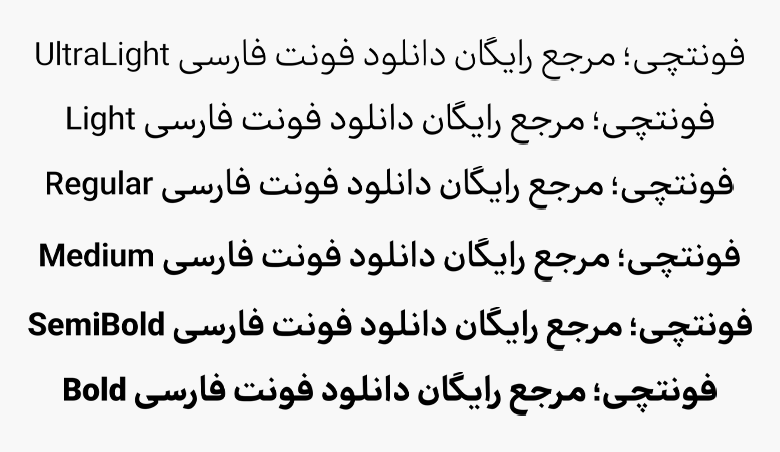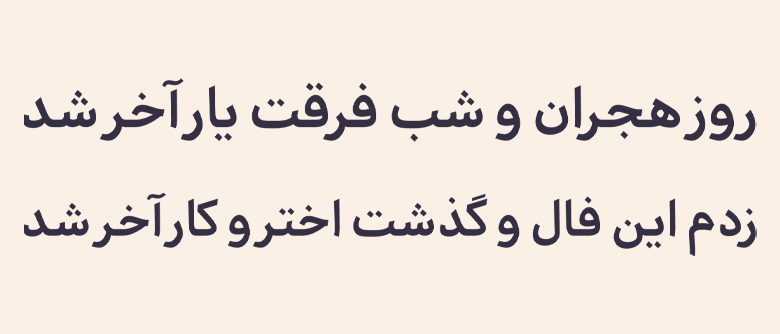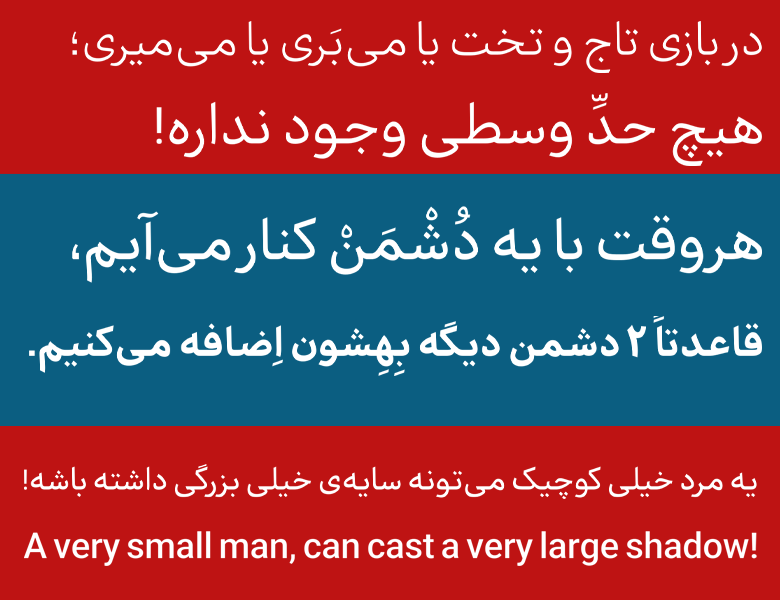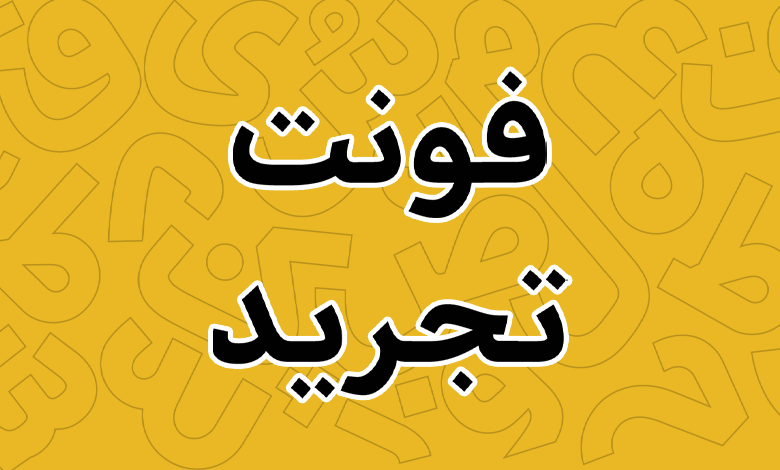
فونت تجرید (Tajrid)
فونت تجرید (Tajrid) یک فونت متن فارسی و عربی است که بر پایه خط نسخ در سال ۱۳۹۲ توسط رضا غفاری طراحی شده و در نهایت در سال ۱۳۹۹ جهت استفاده عمومی منتشر گردیده است. در طراحی این فونت هدف افزایش خوانایی بوده که برای استفاده در متنهای بلند و ساختارهایی که بر اساس اسکرین هستند مناسب باشد؛ از همین رو اگر قرار باشد لیستی از بهترین فونت های وب فارسی داشته باشیم، تجرید یکی از این فونتها است.
در دورهای که فونت تجرید طراحی گردیده بود، فونتهای مناسب وب به تعداد بسیار محدودی بودند که این نیاز همواره برای داشتن فونتی که برای متون فارسی و عربی ساختاری یکپارچه فراهم کند احساس میشد. البته چنین چیزی به این معنی نیست که سایر فونتها این نیازها را برطرف نمیکرد؛ بلکه منظور این است که فونتی که تنظیم نسبت ارتفاع و اندازه حروف و کرسیها در یک ثبات باشد، به تعداد بسیار محدودی بود.
در ادامه این نوشته از سایت فونتچی به نقد و بررسی کامل فونت فارسی نجرید خواهیم پرداخت که علاوه بر این زبان، ساختار بسیار استانداردی با سایر زبانهای خاورمیانهای همچون عربی و اردو دارد. این فونت که دارای ساختاری با پهنای ثابت در بخش اعظم حروف است در ۶ وزن طراحی گردیده است.
معرفی و بررسی فونت تجرید (Tajrid)
در همان نگاه اولی که به فونت تجرید داشته باشید، این حس را منتقل میکند که با یک فونت خاکستری مواجه هستیم. تفاوتی هم ندارد که از کدام وزن این فونت استفاده کنید؛ در تمامی وزنها الگوی کلی این حس را منتقل میکند و به مقدار بسیار محدودی در وزنهای ضخیم از این حس کاسته میشود.
از طرفی دیگر این فونت دارای کنتراست کمتری نسبت به سایر فونتهای متن است و این دقیقا همان چیزی است که در بیشتر فونتهای اینچنین، برخلاف فونتهایی که مناسب عنوان و تبلیغات هستند شاهد آن هستیم.
وزن و استایل فونت تجرید
همانطور که گفتیم فونت تجرید از ۶ وزن پشتیبانی میکند که شامل وزنهای «خیلی نازک، نازک، معمولی، متوسط، نیمه بولد و بولد» است. این فونت بر خلاف سایر فونتهای متن، در تمامی وزنها دارای گلیفهای لاتین است که در یک قلم منفرد (تکی) میشود متن را در هر دو زبان لاتین و فارسی تنظیم کرد.
کاراکترهای اصلی زبان لاتین انگلیسی در این فونت قرار دارد و از همه زبانهایی نظیر عربی، کردی و اردو که از خط فارسی استفاده میکنند نیز پشتیبانی میکند.
ویژگی و امکانات فونت Tajrid
تجرید فونتی مناسب متن است و تفاوتی ندارد که در یک متن کوتاه و عنوان عمچون شعارهای تبلیغاتی از آن استفاده کنید یا اینکه در متنهای بسیار بلند همچون صفحات وب یا چاپ کتاب از این فونت بهره ببرید. در هر حالتی و در همه وزنها، فونت تجرید نیاز شما را برطرف کرده و با توجه به ساختار عالی که از نظر خوانایی دارد، بهترین کارکرد را در دسته فونتهای مناسب متن دارد.
این فونت جدای از مشخصات فوق دارای برخی ویژگیها همچون ترکیبات جایگزین، پشتیبانی از اعداد فارسی و استفاده در انواع وب و اپلیکیشن است که پیش از دانلود فونت تجرید بد نیست نگاهی به آنها نیز داشته باشید.
پشتیبانی از ۴ زبان مختلف
تجرید فونتی است که بر اساس استاندارد جهانی یونیکد طراحی شده است. تمامی گلیفهایی که به هر ساختار حروف و کاراکترها استفاده میشود، برای هر زبان یکه هستند که در این فونت در قالب یک فایل منفرد پیادهسازی گردیده است.
فونت تجرید فارسی برای زبانهای خاورمیانهای یک حالت پیشفرض است که از همینرو کلیه زبانهایی که مبتنی بر حروف فارسی هستند را هم پشتیبانی میکند که از جمله آنها میتوان به زبانهای عربی، کردی و اردو اشاره کرد.
در خصوص زبانهای لاتین همچون انگلیسی نیز همین ساختار یکپارچه و در قالب یک فونت منفرد پیاده سازی شده است که در حالت کلی شما با نصب یک فونت منفرد، میتوانید به تمامی کاراکترهای فارسی، انگلیسی و سایر زبانهایی که این فونت پشتیبانی میکند دسترسی داشته باشید.
مجموعهای از اعداد جداول اروپایی (لاتین) و سمبلها نیز در این فونت پیادهسازی شده که بر اساس صفحه کلید انتخابی، زبان یا استفاده از charmap در سیستم عامل میتوانید به این ترکیبات نیز دسترسی داشته باشید.
دارای حروف و ترکیبات جایگزین
این فونت در برخی حروف دارای چند ساختار مختلف است که میتوانید به شکل متفاوتی چنین حروفی را طراحی کنید. حروفی همچون «الف، ه و ی» در این فونت از چند حالت مختلف پشتیبانی میکنند که برای زبان فارسی و سایر زبانهای خاورمیانهای امکان تایپ کلمات را در چند حالت به شما خواهند داد که میتواند در میحث طراحی روی پیادهسازی خلاقانه متون موثر باشد.
در زبان عربی این ترکیبات در حالتی که در حروف «ه، ی» که دارای دو نقطه در زیر یا بالا هستند نیز وجود دارد که استاندارد بین المللی در آن رعایت شده باشد.
جدا از حروف، برخی ترکیبات نیز از این ساختار پشتیبانی میکنند که برای حروف «ـه، ـی» قابل استفاده است. کلماتی که به این دو حرف منتهی شوند از این جهت قابل تایپ به چند شکل متفاوت هستند. حرف «ه» در میانه کلمات نیز این ویژگی را دارد.
پشتیبانی کامل از اعداد و اعراب
قابلیت دیگر فونت تجرید پشتیبانی از اعداد فارسی و لاتین بر حسب نوع زبان است. در زبان عربی که اعداد «۴، ۵ و ۶» ساختاری متفاوت با اعداد در فارسی (۴، ۵ و ۶) دارد، تایپ اینگونه اعداد متفاوتتر از زبان فارسی است.
در هر دو زبان و سایر زبانها نظیر اردو نیز امکان استفاده از اعراب هر زبان و همچنین برخی کاراکترها و سنبلها که گاها برای تزئین متن مورد استفاده قرار میگیرند قابل استفاده است.